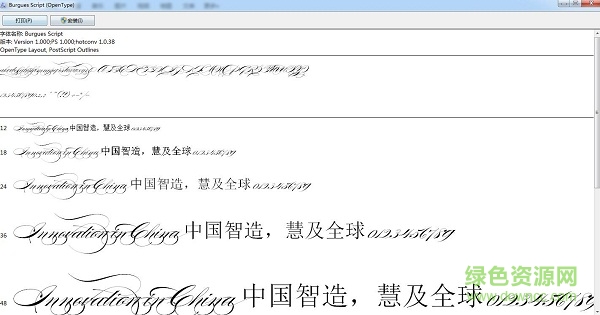
burgues script字體是非常時(shí)尚的一款英文花體字體,線若游絲,靈動流暢,有點(diǎn)像中文的草書字體,可以用于藝術(shù)設(shè)計(jì)、影視海報(bào)等方面,表現(xiàn)力強(qiáng),小伙伴們快來下載吧!
花體字母是有一定的斜度的,整齊的排版也是很重要的因素,字母的長寬比例更是有嚴(yán)格的要求,屬于基礎(chǔ)。
由于不是方塊文字而是字母文字,在文字整體造型的豐富性、多變性、靈活性和書家的自由性方面遠(yuǎn)小于我們的傳統(tǒng)中文書法,所以要達(dá)到視覺的美學(xué)效果及作品的多樣性,guideline起著關(guān)鍵的作用。